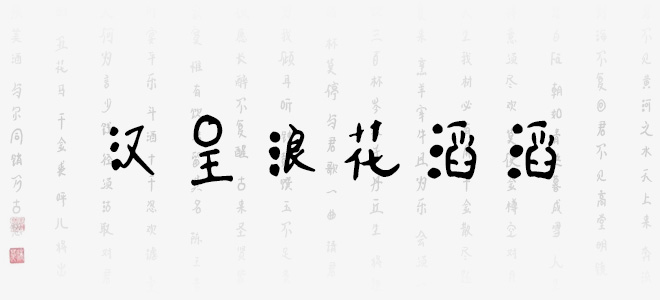
漢呈浪花滔滔該字體整體看上去非常的可愛,字形筆畫看上去較為隨意,但是就是因?yàn)檫@種隨意才讓字體的視覺(jué)效果非常出眾,可以很好的應(yīng)用于文本裝潢、信息展示、網(wǎng)頁(yè)設(shè)計(jì)、篆刻制模、數(shù)據(jù)制作、裝潢設(shè)計(jì)、計(jì)算藝術(shù)設(shè)計(jì)、視覺(jué)設(shè)計(jì)、字帖等一切合法應(yīng)用場(chǎng)景,有喜歡的朋友可免費(fèi)下載收藏。
漢呈浪花滔滔